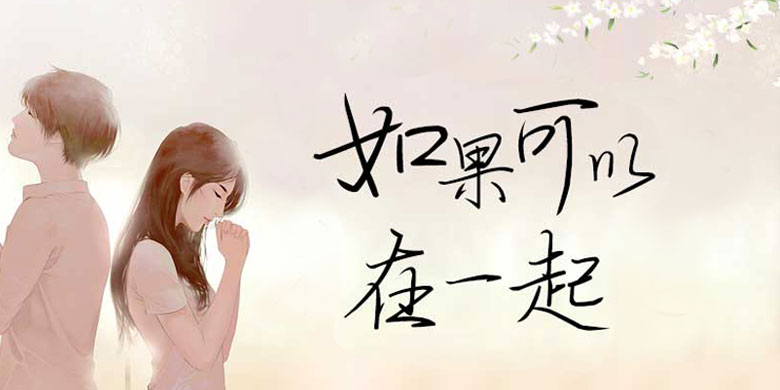
方正手迹-如果可以在一起
方正手迹-如果可以在一起,这款字体结构工整、笔画清晰,兼顾美观与易读性,适用于标题、正文、海报、包装、LOGO 等多种场景。字形优雅稳定,风格百搭耐看,适配日常排版与创意设计,让文字呈现更舒适、更具质感。方正手迹-如果可以在一起一笔一画,皆是细节,以均衡的比例、流畅的线条打造舒适视觉体验,字形端正大气,风格简约现代。无论是商业设计、品牌宣传还是日常排版,都能轻松驾驭,让文字更有格调与力量。方正手迹-如果可以在一起字体下载。
如果可以在一起是一款潇洒的手写体,笔画飘逸舒展,笔锋锐利,既有坚硬刚强的感觉,又有潇洒舒展的感觉。适用于文艺类的书刊、品牌广告和产品包装设计,以及社交网络的个性化用字。